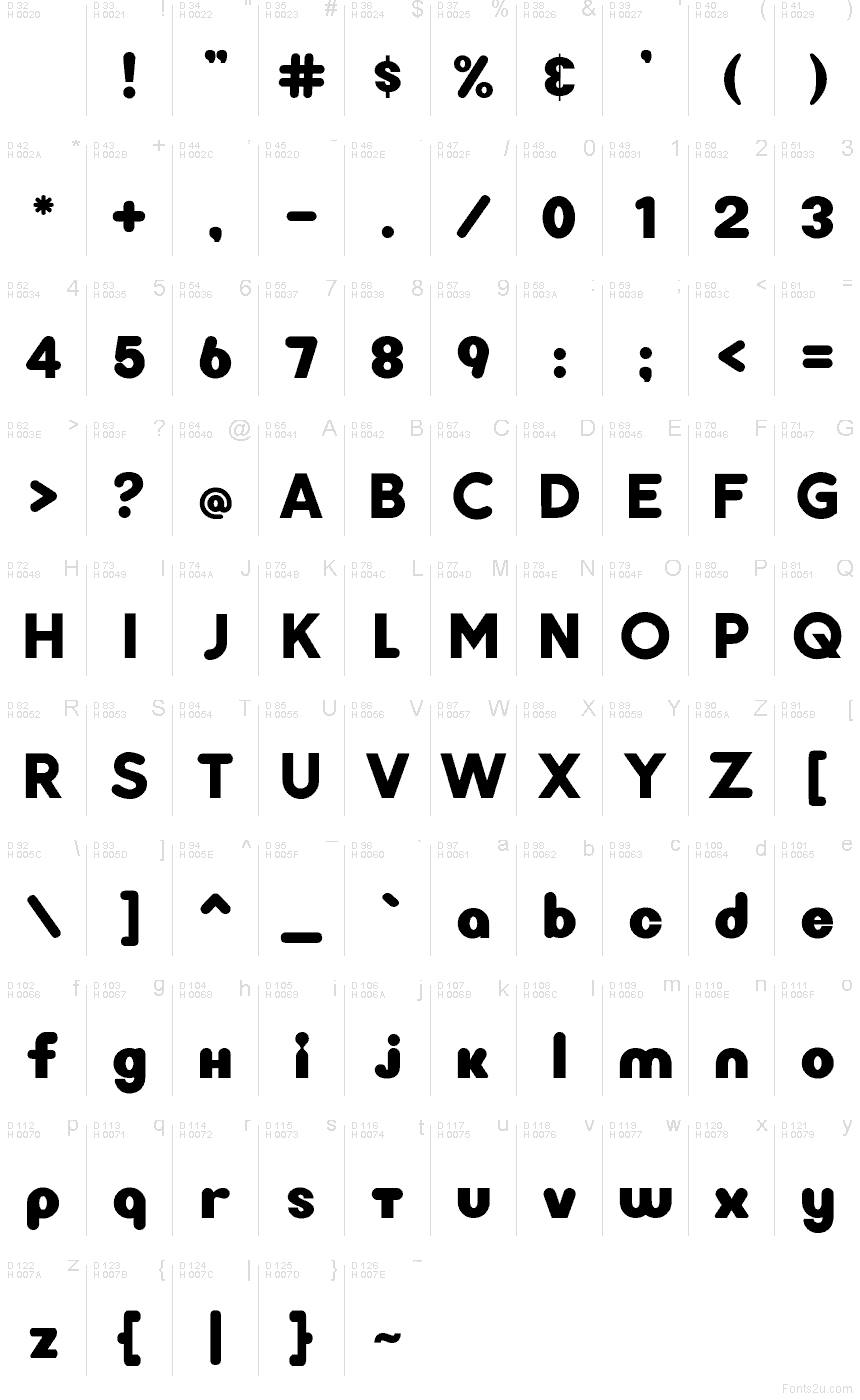
Litebulb Forward
Litebulb Forward é uma fonte display arredondada e gratuita da soloType, que usa formas circulares amplas e verticais curtas para conferir às letras uma silhueta compacta, quase iluminada. As curvas largas e os formatos limitados fazem com que cada caractere pareça denso e robusto, com um ritmo gráfico suave que mantém a coesão em todo o design.
Essa forma densa e levemente saltada é perfeita para pôsteres, telas de abertura de apps, capas de álbuns, marcas voltadas ao público infantil e cabeçalhos curtos em redes sociais, onde uma fonte sem serifa comum pareceria sem graça. Ela também é ideal para ancorar logotipos e embalagens, especialmente quando você busca um bloco de texto amigável que seja lido mais como um objeto gráfico do que como um texto comum.